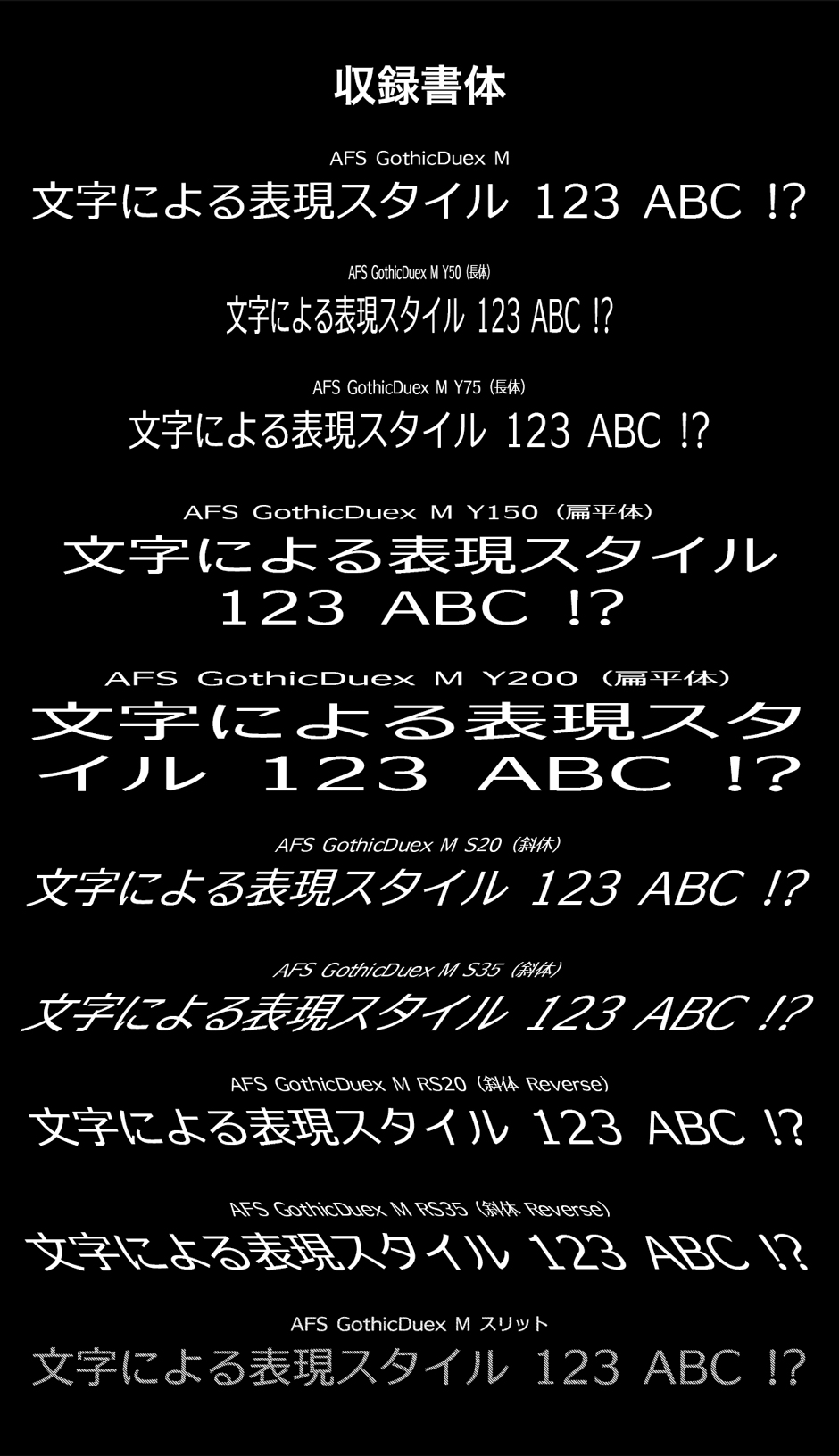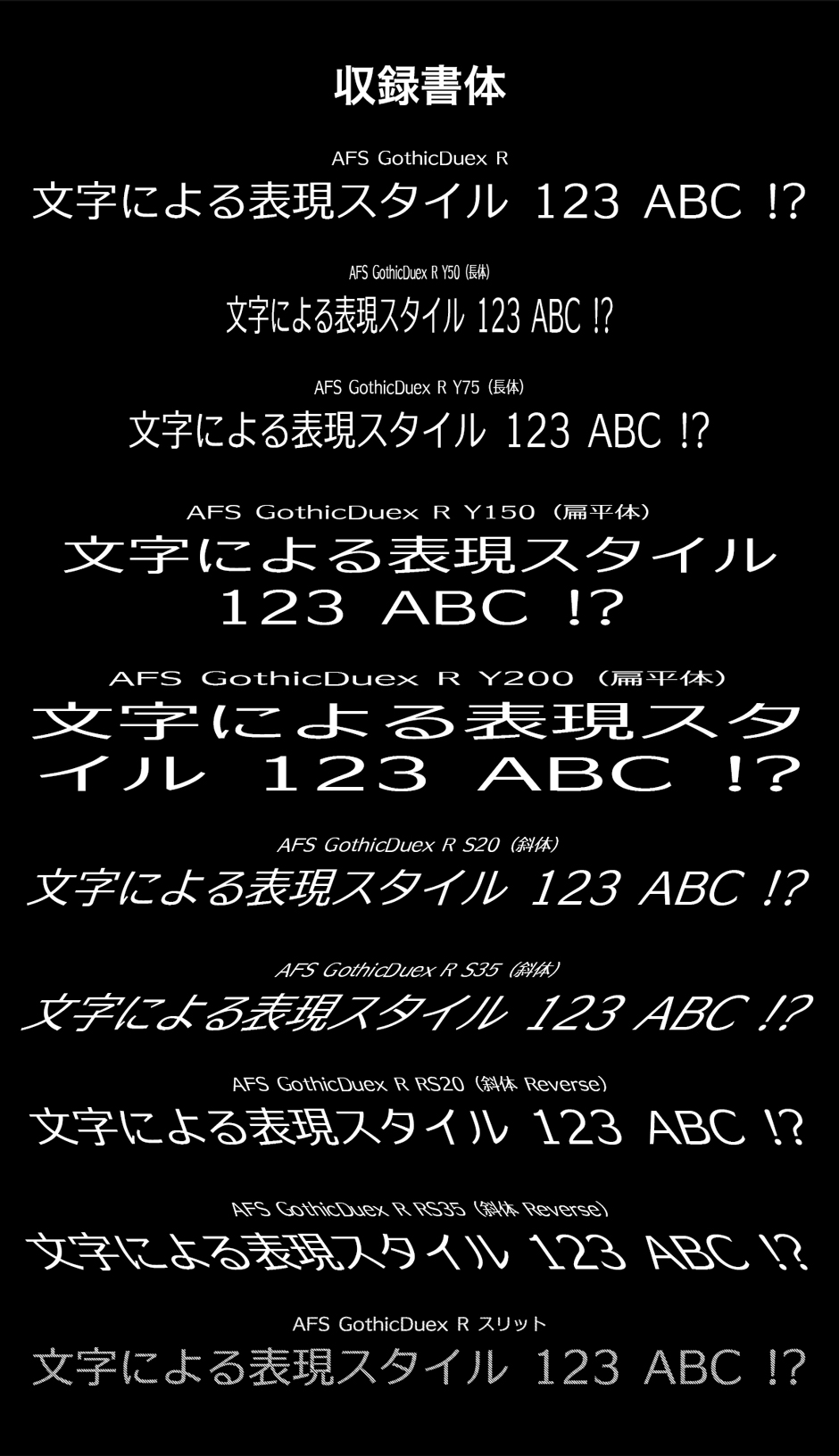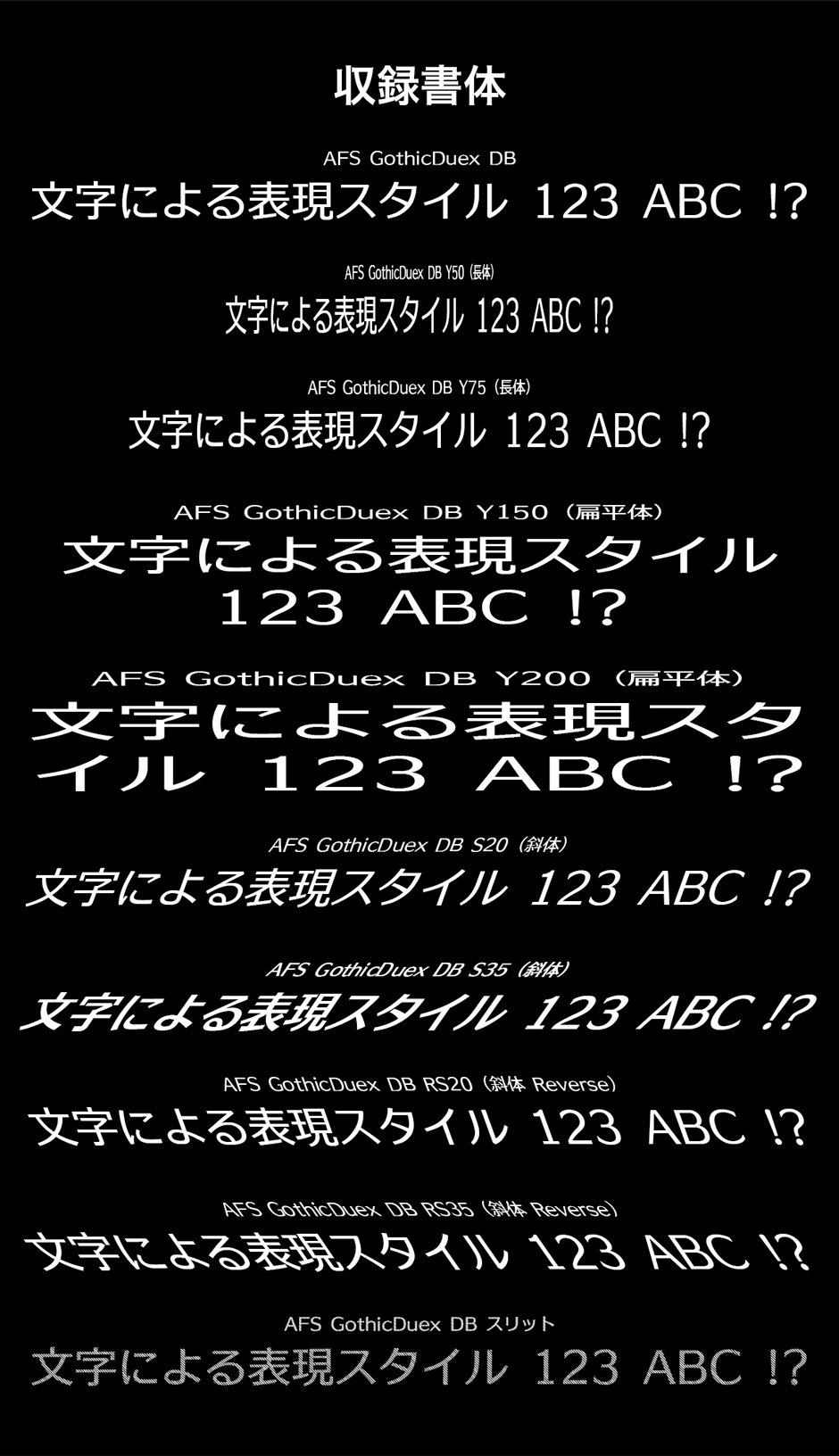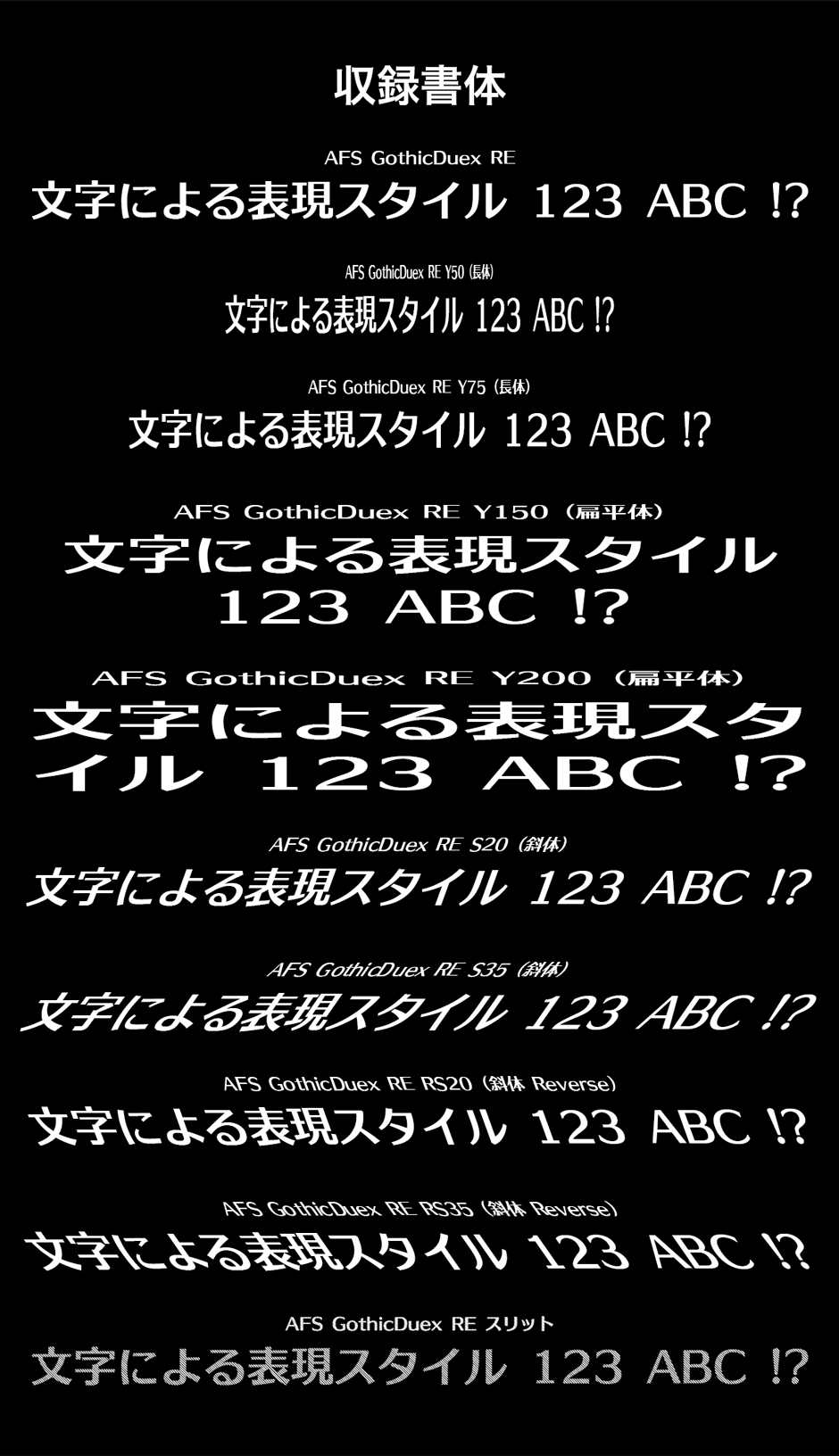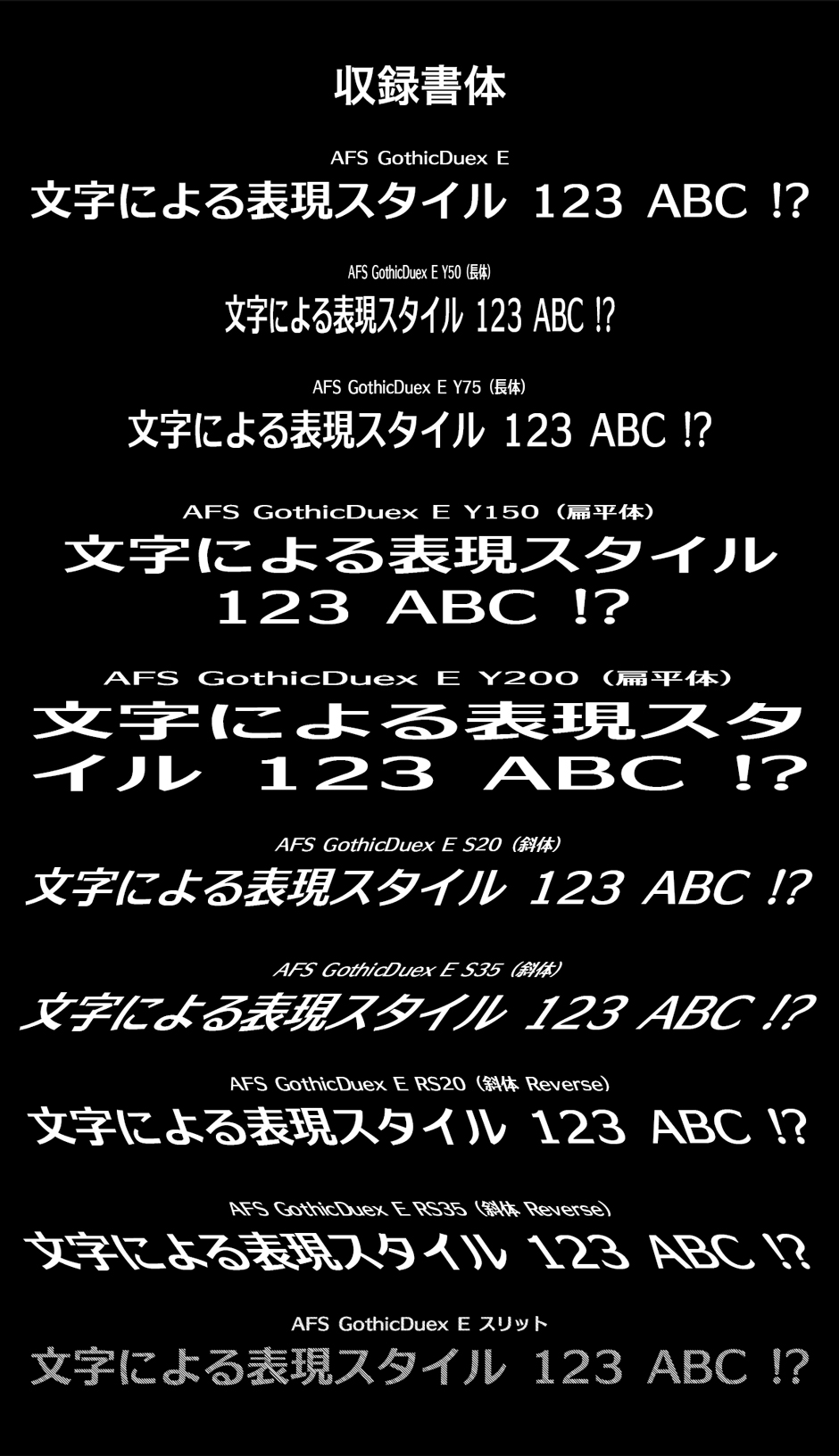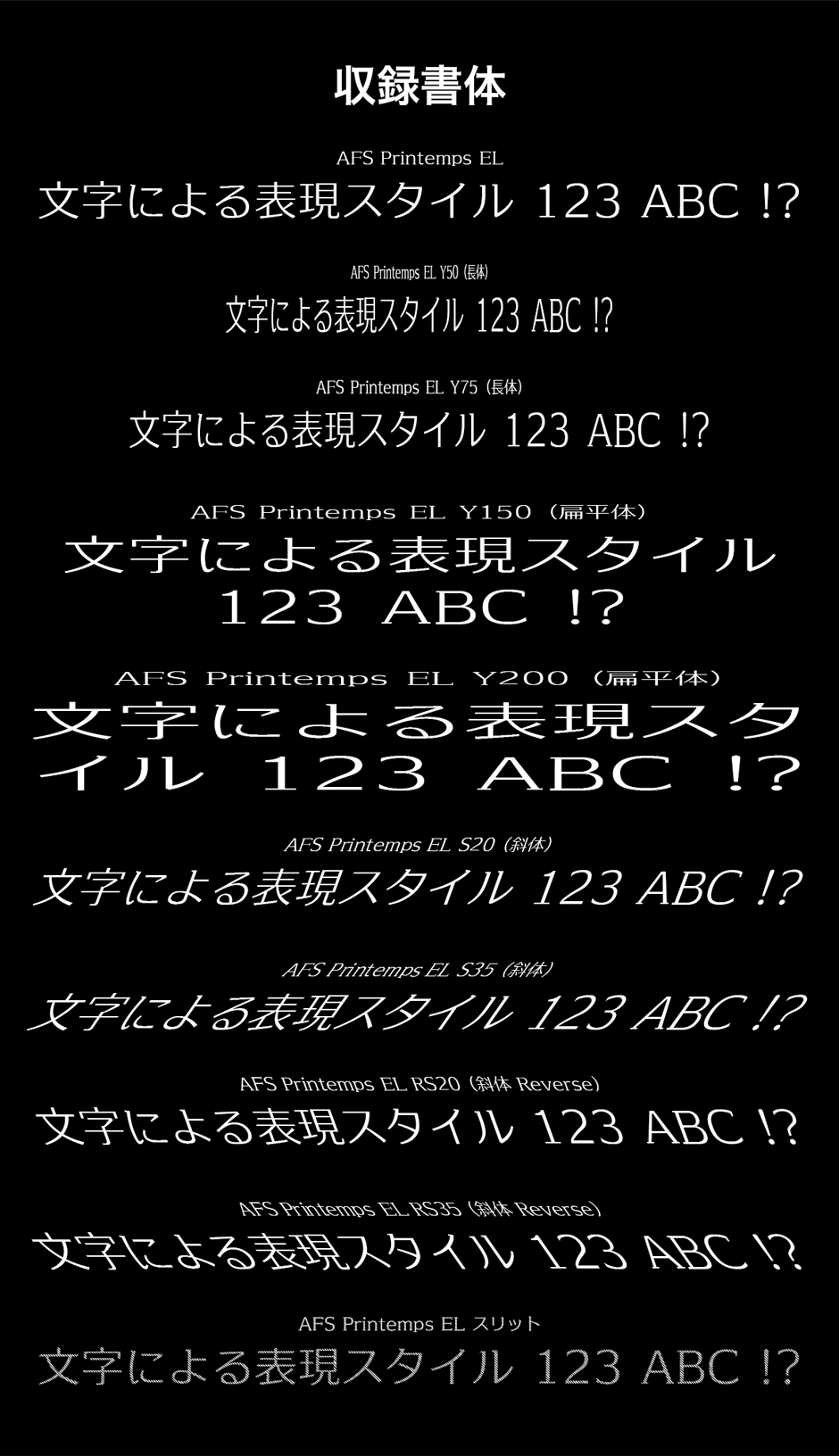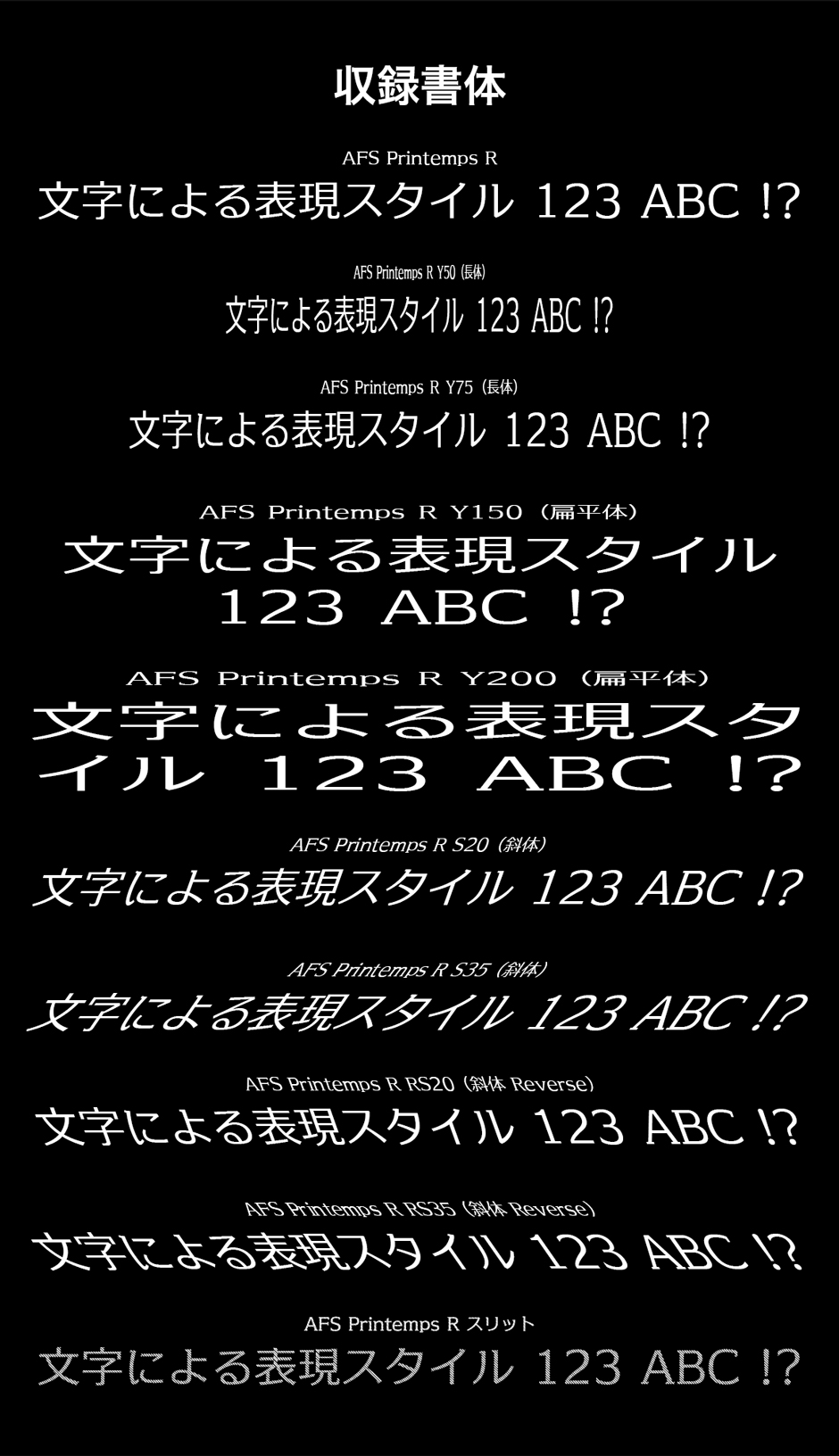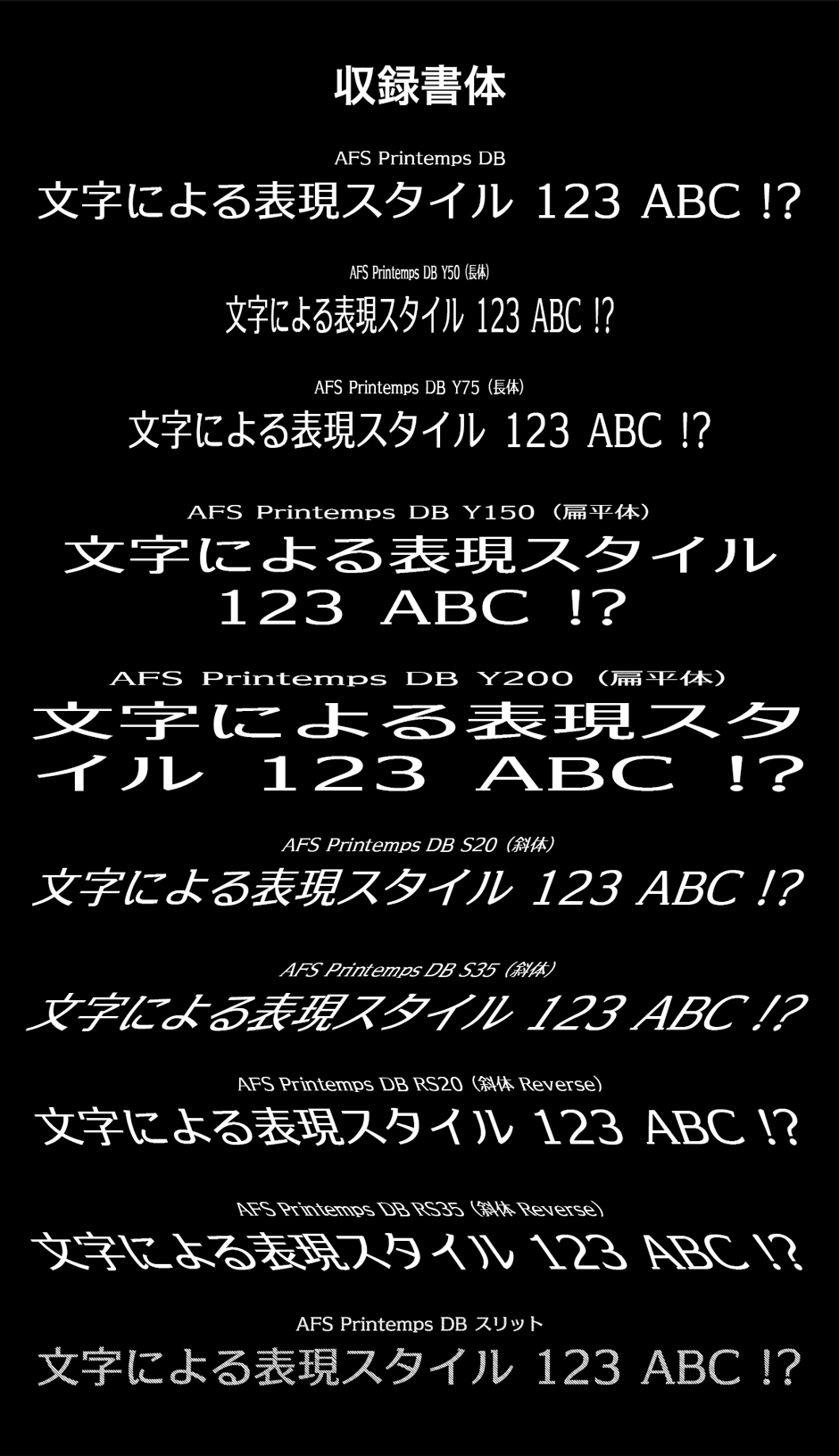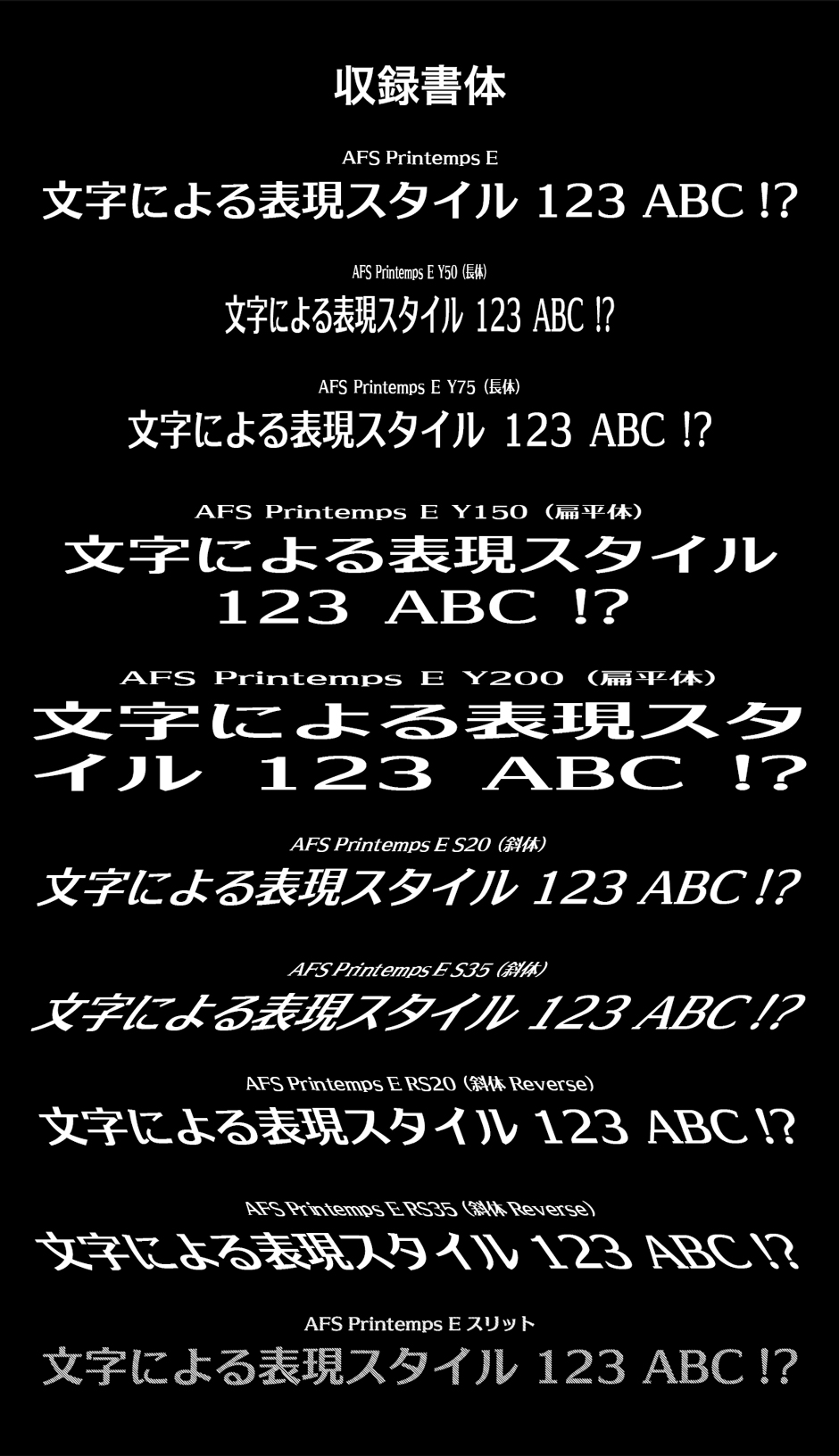
「大活躍!コミックフォントコレクション」の気になる中身
AFSコミックフォントシリーズ
AFSコミックフォントシリーズはアニメ・コミック表紙向けフォントとして、株式会社ネットユーコムが開発する目的別専用フォント。基本書体はWindowsOS標準搭載メイリオフォントデザイナーの鈴木竹治によるデザインを採用しています。
大活躍!コミックフォントコレクションには、AFSコミックフォントシリーズから、AFSコミックおぼろとAFSコミッククロスを収録。袋文字の加工済みで動作環境を選ばず利用でき、ウェブフォントにも対応しているのがポイントです。
さらにコミック・同人誌のセリフで使えるアンチック体も特別に収録。横組み向けの通常版と、縦組みに適した小仮名版の2種類を収録しています。
- AFS アンチックバーズアイ E – 2書体: 通常/小仮名『.TTF』
- AFS コミッククロス E – 4書体:『.TTF』『.WOFF』(共にJIS90/ 2004)
- AFS コミッククロス U – 4書体:『.TTF』『.WOFF』(共にJIS90/ 2004)
- AFS コミックおぼろ 1 – 2書体:『.TTF』『.WOFF』
- AFS コミックおぼろ 2 – 2書体:『.TTF』『.WOFF』
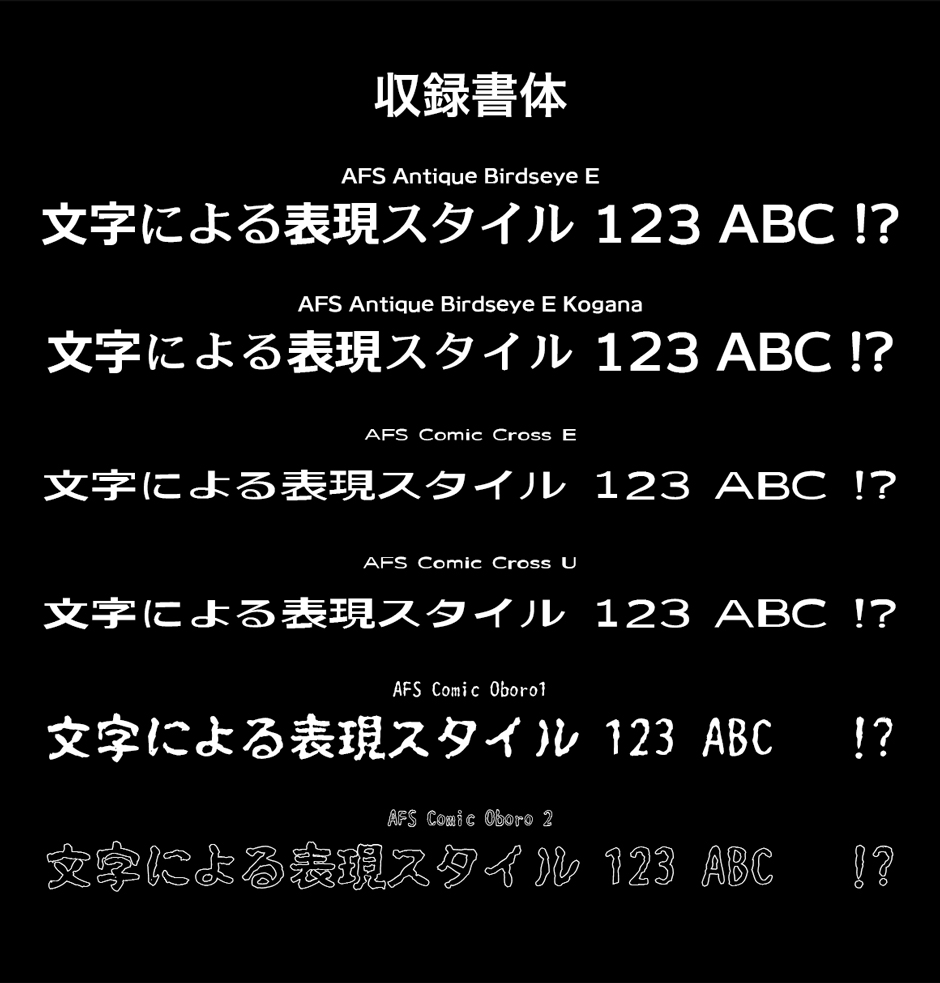
AFS加工済みフォントシリーズ
AFS加工済みフォントシリーズは、株式会社ネットユーコムがお届けする目的別専用フォント。基本となる正体と、それぞれに対して加工 (長体・扁平・左斜体・右斜体・スリット)を施しています。
- AFS ゴシックドゥ M – 10書体:『.TTF』正体/斜体/左斜体/長体/扁平体/スリット
- AFS ゴシックドゥ R – 10書体:『.TTF』正体/斜体/左斜体/長体/扁平体/スリット
- AFS ゴシックドゥ DB – 10書体:『.TTF』正体/斜体/左斜体/長体/扁平体/スリット
- AFS ゴシックドゥ RE – 10書体:『.TTF』正体/斜体/左斜体/長体/扁平体/スリット
- AFS ゴシックドゥ E – 10書体:『.TTF』正体/斜体/左斜体/長体/扁平体/スリット
- AFS プランタン EL – 10書体:『.TTF』正体/斜体/左斜体/長体/扁平体/スリット
- AFS プランタン R – 10書体:『.TTF』正体/斜体/左斜体/長体/扁平体/スリット
- AFS プランタン DB – 10書体:『.TTF』正体/斜体/左斜体/長体/扁平体/スリット
- AFS プランタン E – 10書体:『.TTF』正体/斜体/左斜体/長体/扁平体/スリット